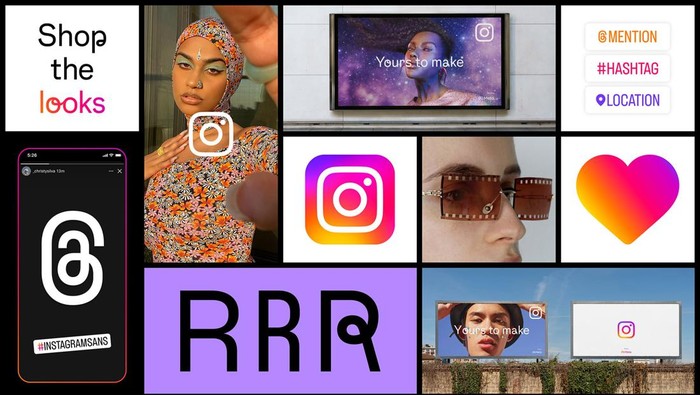
Instagram Bikin Font Baru untuk Reels dan Stories
Font baru Instagram
Instagram Ciptakan Font Baru untuk Reels dan Stories Foto: Dok. Instagram
Instagram menciptakan font baru bernama Instagram Sans yang akan hadir di Reels dan Stories. Font baru ini dihadirkan sebagai bagian dari penyegaran visual untuk branding Instagram.
Selain font baru, penyegaran ini juga membawa logo baru yang lebih berwarna dan layout marketing dengan layar penuh. Instagram mengatakan penyegaran ini dirancang untuk mendorong evolusi yang berkelanjutan dan membantunya menciptakan pengalaman yang lebih mendalam dan inklusif.
Desain font baru ini terinspirasi oleh logo Instagram. Dalam keterangan resminya, Instagram mengatakan font ini terinspirasi oleh persegi (square) dan lingkaran (circle) atau 'squircle'.
Instagram mengatakan font Instagram Sans merupakan hasil kremix kontemporer dari gaya grotesque dan geometris. Beberapa font baru yang dikenalkan Instagram antara lain Instagram Sans Regular, Bold, Light, Medium, Condensed, dan Condensed Bold.
"Instagram Sans adalah cara baru bagi komunitas global kami untuk mengekspresikan dirinya di Instagram di tempat-tempat seperti Stories dan Reels," kata Instagram dalam keterangan resminya, seperti dikutip dari TechCrunch, Selasa (24/5/2022).
Aplikasi milik Meta ini mengatakan mereka telah bekerjasama dengan ahli bahasa untuk membuat typeface baru ini bisa ditampilkan dalam beragam bahasa, termasuk aksara yang ada di bahasa Thailand, Jepang, dan Arab.
Beberapa font yang ditampilkan terlihat normal, tapi ada juga font yang terlihat tidak biasa seperti Instagram Sans Script yang hampir setiap hurufnya ditambahkan aksen meliuk-liuk.
Font baru Instagram Foto: Dok. Instagram
Font yang sedikit aneh ini sepertinya dirancang untuk membuat identitas Instagram semakin menonjol. Setidaknya jika ada konten Reels atau Stories yang menggunakan caption dengan font Sans Script akan terlihat jelas bahwa konten itu berasal dari Instagram dan tidak diimpor dari TikTok.
Sedangkan untuk logo barunya, warna gradiennya dibuat lebih cerah untuk membuatnya terlihat lebih terang dan hidup. Terkait layout dengan layar yang lebih penuh, Instagram mengatakan ini dirancang untuk lebih menonjolkan konten dan mengutamakan kesederhanaan.
Layout layar penuh ini diumumkan setelah Instagram dilaporkan sedang menguji coba tampilan feed layar penuh ala TikTok. Dalam uji coba ini, foto dan video ditampilkan secara penuh dengan caption dan komentar ditumpuk di atas konten.